Chatworkのリブランディングで生まれたコーポレートフォント『Chatwork Sans』の開発ストーリー
突然ですが、コーポレートフォントを制定するプロセスをご存知でしょうか?難しそう?時間も費用もかかりそう?そもそもどうやって決めるの?さまざまな疑問をお持ちの方もいるかも知れません。
既存のフォントをコーポレートフォントに指定するケースもあれば、ゼロから新たにフォントを作るケース、既存のフォントをベースにカスタマイズして開発するケースもあります。
今回は、ビジネスチャット「Chatwork」を提供するChatwork株式会社の企業のリブランディングに際し、コーポレートフォントの制作をモリサワがお手伝したお話です。
同社のみなさまに、コーポレートフォントができるまでのストーリーを伺いました。
1. Chatworkの目指す世界観や働き方に共感してもらう
ー 会社では、どんなお仕事をされているのですか?
新免 Chatwork株式会社は、メールや電話、会議・訪問など仕事で必要なコミュニケーションをより効率的にする中小企業向けビジネスチャット「Chatwork」を提供しています。私は、ピープル&ブランド本部のBX(ブランドエクスペリエンス)部に所属しています。クリエイティブチームのチームリーダーとして、ブランドに関わる制作物全体を統括するとともに、プロジェクトの進捗確認などのマネジメントを行っています。
小野寺 主に会社のブランディング開発を行っています。全社総会などの社内向けインナーコンテンツのデザインや、新しい社外向けコンテンツのLP(ランディングページ)制作を手掛けています。
一戸 新免、小野寺と同じくBX部のクリエイティブチームに所属し、デザイナーを務めています。主に、ブランディングのサポートやインナーコミュニケーション、カルチャーブックなどの印刷物をはじめ幅広く担当しています。
ー 2021年の8月にサービスのリブランディングを発表しました。どういった想いからブランドを刷新されたのでしょうか。
新免 一言でいえば、「Chatworkの目指す世界観に共感してもらい、選ばれるサービスにしたい」という想いです。当社がビジネスチャットをリリースしたのは2011年3月のこと。発表当時はサービスの先進性や使い勝手から、多くのユーザー様にご支持をいただきました。
しかし、さまざまな競合サービスが増えてきた昨今は、機能や価格面だけでは選ばれにくくなっていると感じ始めたのです。この間、社員数も大幅に増え、社外への情報発信も増えてきました。
ブランドの一貫性を保ちながら、ユーザーの皆様に当社のサービスを選んでいただくためには、ブランドに関する確固とした軸が不可欠だと考えました。そこから、Chatworkの目指す世界観や働き方に共感してもらうべく、新たなブランド戦略を練っていきました。
2. 約20種類のフォントをピックアップして検証
ー 新たなブランドを確立するために、どのくらいの期間がかかったのですか。
小野寺 プロジェクトがスタートしてから発表するまで、8カ月くらいの時間がかかりました。社内にブランディング開発の知見も少なかったため、社外のブランド戦略の専門会社と協同し、プロジェクトを進めていきました。
私たちの中では、それぞれのChatworkの世界観らしきものを認識していましたが、これを具現化していくことは、非常に難しいものがありました。
最終的なデザインコンセプトは、Chatworkがユーザー1人ひとりにフォーカスし、創造的な働き方を提供するという意味を込めた「Focus & Create Your Vision」と決定しました。
ー リブランディングに合わせ、コーポレートフォントの選定も検討されたそうですね。
新免 当社では、これまでモリサワの「UD新ゴNT」のほか、英字は古典的サンセリフ書体を基本とし、Webサイトにも UD新ゴNT をWebフォントで使っていました。UD新ゴNT を選んだ理由は、丸みを帯びているChatworkのロゴとの相性やフォントとしての視認性の高さなどです。
その一方で、使用するシーンによっては必ずしもベストではないという声もありましたので、フォントの変更も含めた検証に取り掛かりました。
小野寺 社名ロゴとの親和性の観点から約20種類のフォントをピックアップし、会社がよく使うキャッチコピーを当てはめて見え方を検証しましたが、なかなか私たちのイメージにピッタリ合うものはありませんでした。検証を通じて、新フォントのイメージがより固まっていったものの、それに合うフォントに巡り合えずにいました。
3. 既存フォントを利用したカスタマイズフォント
このような課題に対して、モリサワはどのようなソリューションを提案したのでしょうか。当社のChatwork様担当営業の吉野氏と『Chatwork Sans』制作に携わったタイプデザイナーの榛葉氏にも話を聞いてみました。
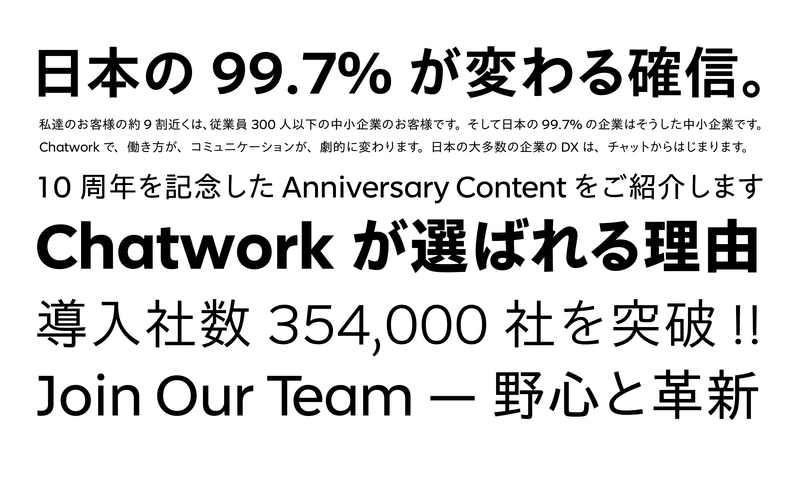
ー フォントの完成まで、どんなフローで進められたのでしょうか?
吉野 ChatworkさんはこれまでUD新ゴNTをお使いいただいていた中でのリブランディングということで、新しいタイプフェイスへの具体的なイメージをお持ちだったことが印象的でした。
今回は限られた時間で最大の効果を発揮すべく、既存フォントのカスタマイズをすることで理想のコーポレートフォント制作を目指すことになりました。
コーポレートフォント完成までのおおまかな流れとしては、はじめにChatworkさんがコーポレートフォントに求めるイメージや要望をヒアリングしました。
「ゴシック体」「和文欧文の印象」「Webで多用したい」「ロゴとの相性」等お聞きした上で、和文と欧文フォントを数種類ご提案しました。この際に、文字のカスタマイズができることや、和文と欧文フォントをひとつに合成することも提案の中に加えました。社名がアルファベットであるため、ニーズを感じたためです。
Chatworkさんにてベースとなるフォントを選定いただき、和文と欧文を合成するため、太さや混植比率のマッチングを調整しました。次に一部の文字をカスタマイズするにあたり複数のサンプルを作成し、Chatworkさんの意見を伺いながら最終的なデザインを決定しました。
ー カスタムフォント制作のポイントを教えてください。
榛葉 一番難しかったのは和欧混植の設計です。それぞれ別々に開発された和文と欧文を合成する必要があったのですが、フォントが使用される環境や用途によって最適な混植比率は変わってきます。今回のコーポレートフォントでは主にコーポレートサイトで本文から見出しまで幅広くお使いになるということでL, R, B, EBの4ウエイトをご用意しました。細いウェイトは文章や長めのキャプションが組めるように和文と欧文の大きさの差を少なく、一方で太いウェイトは大きなサイズでの利用を想定して欧文をやや大きめに設計してコピーや見出しでまとまり感が出るように気をつけました。
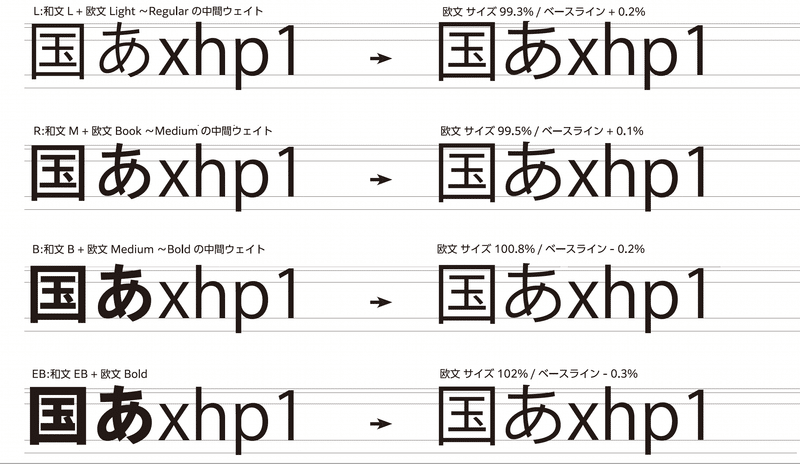
ー デザインのカスタマイズについてはどのような工夫があったのでしょうか?
榛葉 Chatworkさんからのご要望で、アルファベットの「a」と数字の「1」「7」の合計3文字のデザイン改変を行いました。まず「a」についてはロゴデザインにあわせて、double-storey(2階建て)からsingle-storey(1階建て)へと変更しました。
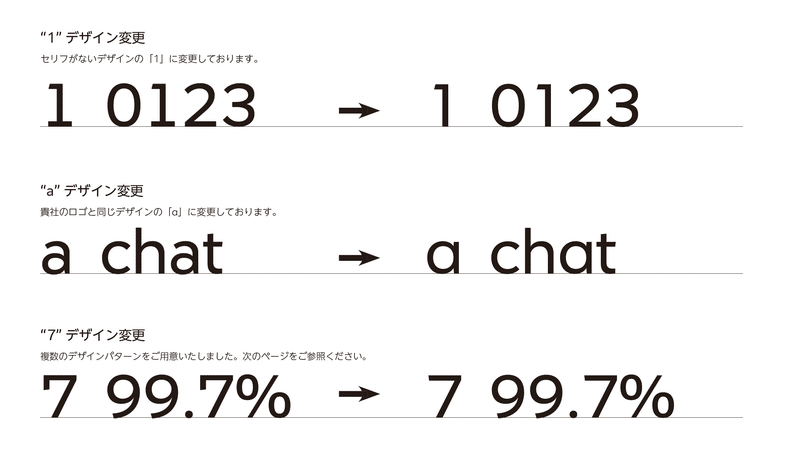
数字の「7」についてはChatworkさんからいくつかデザインパターンを見たいというご要望を頂き、最終的には3種類をご提案し現在のデザインに決定したのですが、実は社内では5種類作成していました。自社製品の制作だと数字のデザインだけでここまで多くのバリエーションを検討することはあまりないので、私自身も多くの気づきがありました。
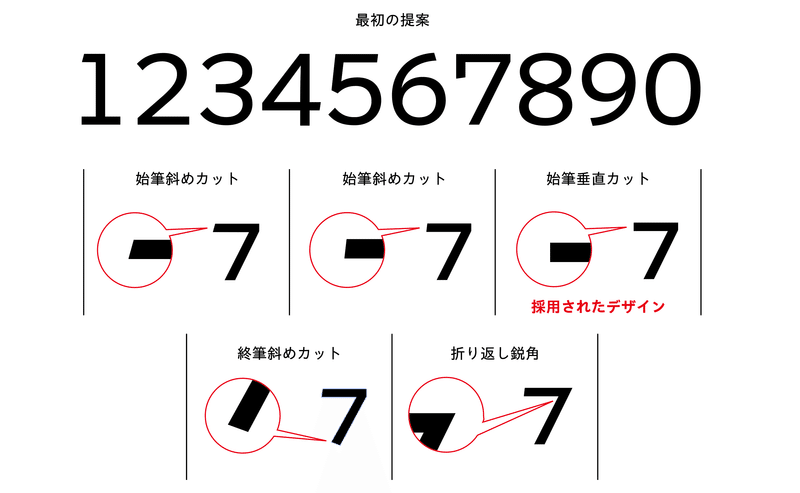
ー 最終的に選定されたフォントはどのような特徴なのでしょうか?
吉野 和文は2021年にリリースされたばかりの「あおとゴシック」、欧文は幾何学的で明るい印象を持つサンセリフがベースとなっています。あおとゴシックはWebサイトをはじめ主にオンスクリーン利用を想定したややモダンでこぶりな、モダンゴシック体です。
これまでChatworkさんで使用されていたUD新ゴNTと比べ、より長文組版に最適化されていることもあり、様々なコンテンツを一貫してオンラインで展開される用途に合致したのではと考えています。
欧文はジオメトリックサンセリフと呼ばれるジャンルで、Chatworkさんのロゴともテイストが近いことが採用の決め手となりました。ロゴタイプとコーポレートフォントに統一感をもたせることで発信されるメッセージのトーンにも一貫性が生まれます。
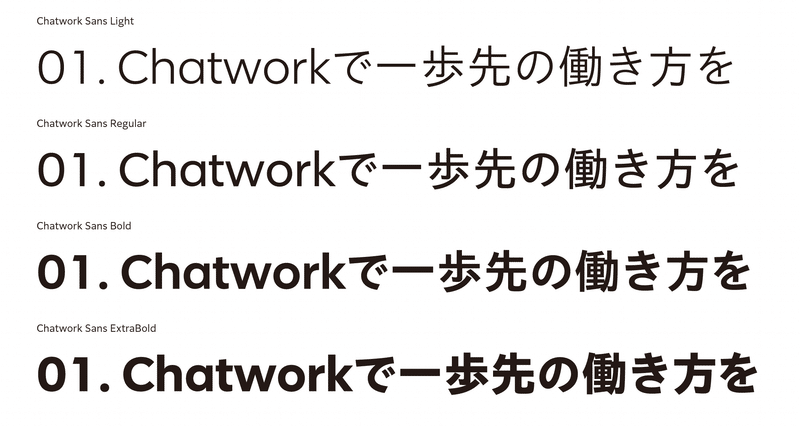
新免 書体デザインがおおよそ完成した際にフォントの名前はどうしようという話になり、①Chatworkの名を冠する、②呼びやすさを重視する――などの条件に当てはまる『Chatwork Sans』と命名しました。
一戸 社内でも、自社の名前を冠したフォントが使用できるとあって、盛り上がりました。新フォントは、程よく字面が空いており、文字の癖も感じません。フォント自体にかっこよさがあり、Chatworkのブランドイメージに非常にマッチしていると思います。
新免 当社の社名は「Chatwork株式会社」で英語と日本語が混ざっています。実務上、それぞれをバラバラで使用するのは大変だし、1つのフォントで運用できる利便性と、Webフォントとして使用できる点も、選定にいたった理由です。完全オリジナルでフォントを制作するとコストも時間もかかると聞きましたが、既存フォントのカスタマイズなら、これらを抑えながらオリジナリティも加えたフォントが制作できることを実感しました。
4. オリジナルのコーポレートフォントでブランド力向上へ
ー 新しいフォントは、どのようなものに使われていきますか。
一戸 Webサイトや印刷物、またその他の制作物、ほとんどすべてのプロダクトに『Chatwork Sans』を使用していく予定です。従業員向けに、社内のミッション・ビジョン・バリューなどをより深く理解してもらうために、カルチャーブックを作成していますが、こちらにも『Chatwork Sans』を使用しています。
新免 まずは、日本の製品サイトやコーポレートサイトに新フォントを反映し、フォントの統一に取り組んでいきたいと思います。製品サイトやコーポレートサイトはWebフォントを採用しているので、閲覧するデバイスに依存せず、『Chatwork Sans』で表示することができます。
小野寺 時間をかけてChatworkのブランディングを固めましたので、今後は、社内への浸透に努めていきたいと思います。社内でアセット制作を担当していますが、まだ反映しきれていない媒体も少なくないため、そこも更新
し、Chatworkサービスのブランド向上に取り組んでいきたいと思います。